如何将新字体添加到InDesign中
dsbkAdobe InDesign可用于创建各种打印材料,包括书籍、海报、传单和小册子。在电脑上安装新字体可以使它在InDesign和其他应用程序中使用。如果你使用的是2019版或更高版本的InDesign,那就可以在不关闭应用的情况下从Adobe安装免费字体。本文教你如何在Windows或macOS电脑上安装新字体,并在InDesign中使用这些字体。
Adobe InDesign可用于创建各种打印材料,包括书籍、海报、传单和小册子。在电脑上安装新字体可以使它在InDesign和其他应用程序中使用。如果你使用的是2019版或更高版本的InDesign,那就可以在不关闭应用的情况下从Adobe安装免费字体。本文教你如何在Windows或macOS电脑上安装新字体,并在InDesign中使用这些字体。
在InDesign 2019中激活Adobe字体
1打开电脑上的InDesign。如果是Mac,它就在“应用程序”文件夹中,如果是Windows,那它就在“开始”菜单中。2019版的InDesign允许你在应用程序内部激活数千种预授权的免费字体。
2点击“字符”面板中的寻找更多。如果你没有看到这个面板,按⌘ Cmd+T(Mac)或Ctrl+T(PC)来打开它。寻找更多按钮就在字体选择菜单下面。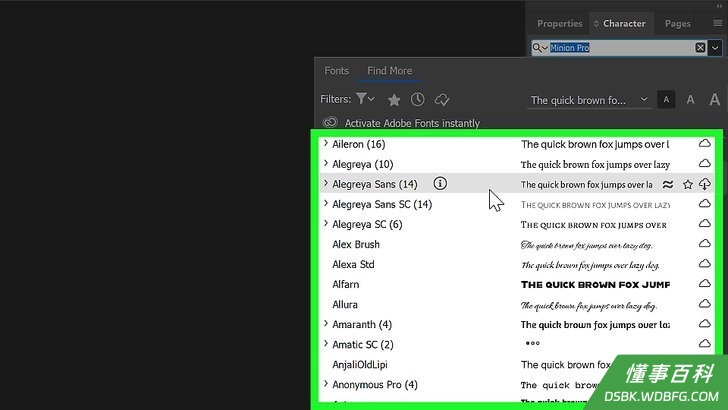
3浏览字体列表。出现的字体都可以免费下载。将鼠标悬停在列表中每种字体的名称上就可以看到预览。
4点击字体旁边的“下载”按钮。每种字体的名称右侧都有一个对应的云形图标。如果你看到在字体旁边有一个带有向下箭头的云形图标,那就说明这个字体尚未安装。点击图标进行下载。- 当字体可以在InDesign中使用时,云上的箭头将变成一个复选标记。
- 安装的字体也可以在Illustrator 2019和其他各种Adobe应用程序中使用。
在Mac上下载新字体
1将字体下载到电脑上。许多网站都免费提供字体供个人下载使用。你可以通过最喜欢的搜索引擎来搜索这类网站,然后浏览字体。在找到想要的字体后,点击下载按钮把它保存到电脑上。一些常见的字体下载网站包括: https://www.dafont.com 、 https://www.1001freefonts.com 和 https://www.myfonts.com 。- InDesign支持以下字体类型:OpenType、TrueType、Type 1、Multiple Master和Composite。如果下载的字体要求你在下载之前选择一种格式,那就先进行选择。
2关闭InDesign。在安装字体之前,保存InDesign中的工作,然后关闭应用程序。
3在Mac上打开“访达”。图标是一个带有两种颜色的笑脸,在“程序坞”中。
4浏览到包含下载字体的文件夹。默认情况下,下载的文件应该会保存到下载文件夹。如果你下载的是压缩文件(通常以.zip结尾),双击文件来解压缩。- 下载的字体文件扩展名通常为.otf或.ttf。
5双击字体文件。这样将打开一个显示字体预览的对话框窗口。
6点击安装字体。它是对话框窗口右下角的蓝色按钮。这样就会将字体安装到Mac上。
7打开InDesign。你可以在“应用程序”文件夹中找到它。你安装的字体将出现在“字符”面板中的“字体”菜单中。- 你可以在InDesign中浏览字体了。
在PC上下载新字体
1将字体下载到电脑上。许多网站都免费提供字体供个人下载使用。你可以通过最喜欢的搜索引擎来搜索这类网站,然后浏览字体。在找到想要的字体后,点击下载按钮把它保存到电脑上。- InDesign支持以下字体类型:OpenType、TrueType、Type 1、Multiple Master和Composite。如果下载的字体要求你在下载之前选择一种格式,选择其中一种格式。
2关闭InDesign。在安装字体之前,保存InDesign中的工作,然后关闭应用程序。
3右击“开始”菜单,并选择文件资源管理器。这样将打开电脑文件浏览器。
4浏览到包含下载字体的文件夹。默认情况下,下载的文件应该会保存到下载文件夹。如果你下载的是压缩文件(通常以.zip结尾),右击文件,选择全部解压,然后点击解压。这样将解压一个包含字体的文件夹,或者直接解压字体文件。- 下载的字体文件扩展名通常为.otf或.ttf。
5右击字体文件并选择安装。字体将开始安装。
6打开InDesign。你可以在“开始”菜单中找到它。安装的字体将出现在“字符”面板中的“字体”菜单中。
- 字体有几大类。“衬线字体”(带有笔画装饰)和“无衬线字体”(无笔画装饰)是最常见的。常见的衬线字体包括Times New Roman和Garamond。常见的无衬线字体字体包括Arial和Helvetica。字体也可以具有装饰性,这意味着它们比标准的衬线字体或无衬线字体具有更独特的外观。装饰型字体的例子包括Papyrus和Playbill。